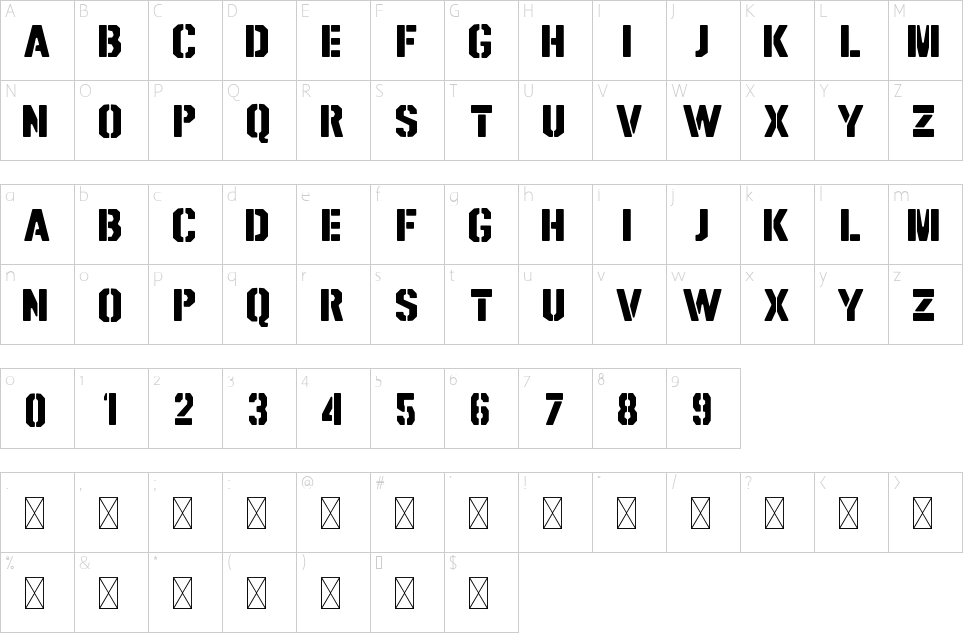
Descubra a SGT John O font, uma elegante e moderna fonte que certamente vai adicionar um toque único ao seu design. Desenvolvida pelo designer Tokokoo, esta fonte já foi baixada mais de 8500 vezes, demonstrando sua popularidade entre criadores e designers digitais. SGT John O foi projetada para oferecer uma aparência sofisticada que se adequa perfeitamente a títulos e textos em geral. Perfeita tanto para criações no Windows quanto no Mac, esta fonte gráfica livre é um excelente complemento para qualquer projeto de design. Descubra por si mesmo como SGT John O pode moldar sua próxima arte digital.